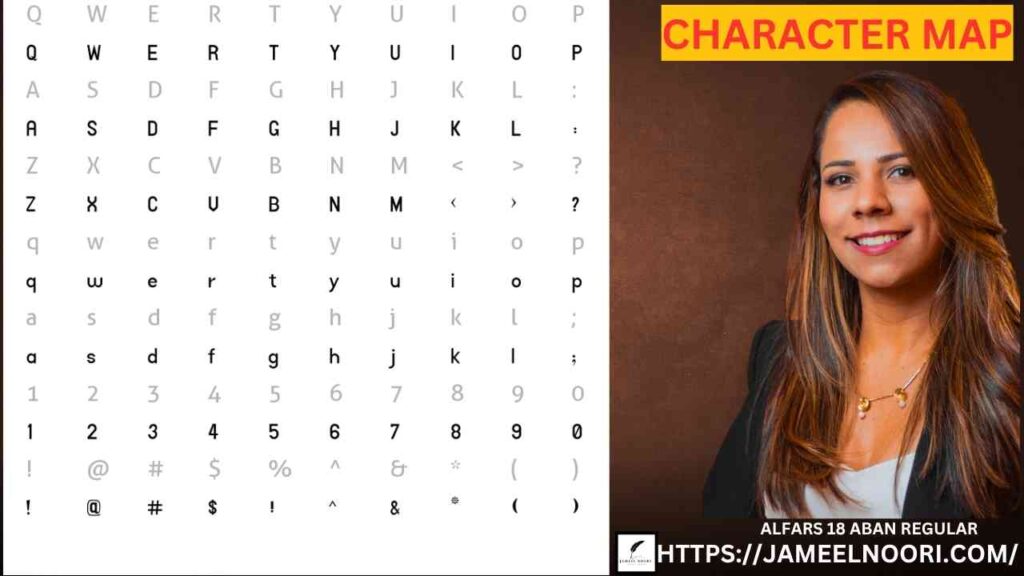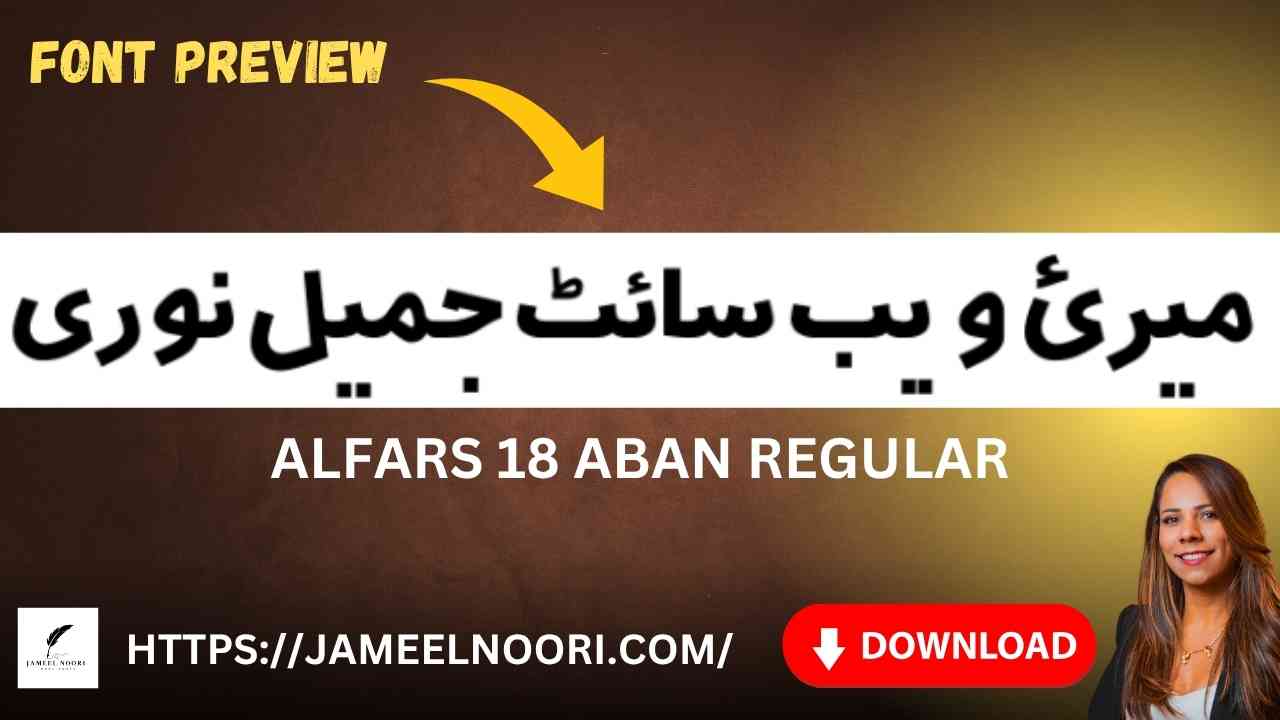
AlFars Aban Font Ke Features
- ✅ Smooth & balanced Urdu typography
- ✅ Ideal for print aur digital designs
- ✅ Stylish look with traditional readability
AlFars Aban Urdu Font Kahan Use Ho Sakta Hai?
- ✅ Urdu poster aur banner design mein
- ✅ Social media thumbnails aur YouTube Urdu content ke liye
- ✅ InPage alternative Urdu typing tools mein
- ✅ Urdu poetry & calligraphy art ke liye
AlFars 18 Aban Regular Urdu Font ek zabardast blend hai style aur readability ka.. Agar aap apne Urdu projects ko classy touch dena chahte hain to yeh font zaroor try karein.. Yeh fast download hota hai, lightweight hai aur har platform par seamless kaam karta hai.